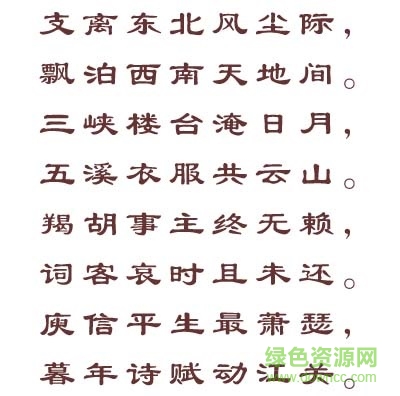
雅坊簡隸字體
雅坊簡隸字體是看上去非常舒服的隸書字體,橫長豎短,結(jié)構(gòu)工整,骨絡分明,不論是用于廣告設計還是正文排版效果都非常好,需要的小伙伴快來綠色資源網(wǎng)下載吧!
雅坊簡隸字體特點
該字體偏粗,結(jié)構(gòu)清晰,支持各大電腦系統(tǒng)安裝使用,可應用于平面設計、名片設計、廣告創(chuàng)意、印刷包裝等領域